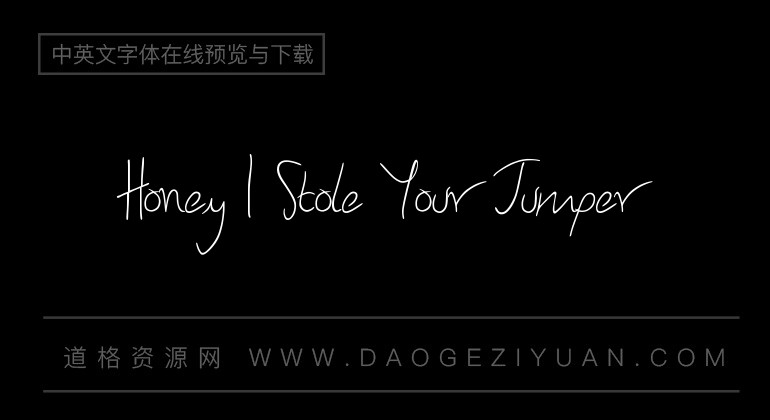
Honey I Stole Your Jumper
Honey I Stole Your Jumper 是一种手写风格的字体,该字体的设计师是 Misti's Fonts。这种字体看起来非常自然和流畅,它的每一个字母都有一种轻松的感觉,仿佛是由手写而成。它的字母间距较小,笔画线条较细,通常用于设计温馨、亲密和浪漫的场景,比如情人节卡片、婚礼邀请函、家庭相册等等。此外,Honey I Stole Your Jumper 字体还带有一点点复古的气息,它的外观与80年代和90年代的手写信件非常相似,因此也适用于与怀旧和复古风格有关的设计项目。
Honey I Stole Your Jumper是一款非常不错的手写艺术字体,具有很好的视觉感,适合于文化类的宣传设计、商业类品牌的广告和产品包装设计以及个性化文字排版等较多场景。